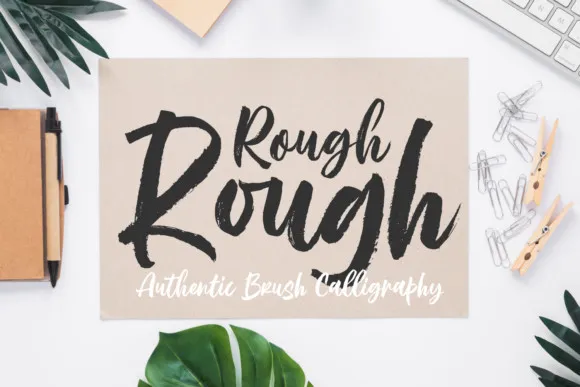
Rough Rough Brush Font – Fonte Grátis
Rough Rough Brush Font
Rough Rough Brush Font é uma fonte script que oferece um toque autêntico do traçado manual com canetão. Perfeita para projetos de design, essa fonte inspira e atrai a atenção com sua sensibilidade romântica e estilo contemporâneo. Criada pelo designer Situjuh, ela transforma qualquer projeto em um destaque. É uma escolha excelente para logos, identidade visual, arte manual, designs de camisas, projetos impressos, capas de livros, álbuns, frases e cartões. O Rough Rough Font Duo traz uma experiência única com seu toque casual e bold, além das alternativas extras e ligaturas que fazem a fonte ainda mais atrativa. Com sua delicadeza romântica e atitude audaciosa, essa fonte é perfeita para diversos aplicativos de design, garantindo um resultado impecável em qualquer projeto que escolha.